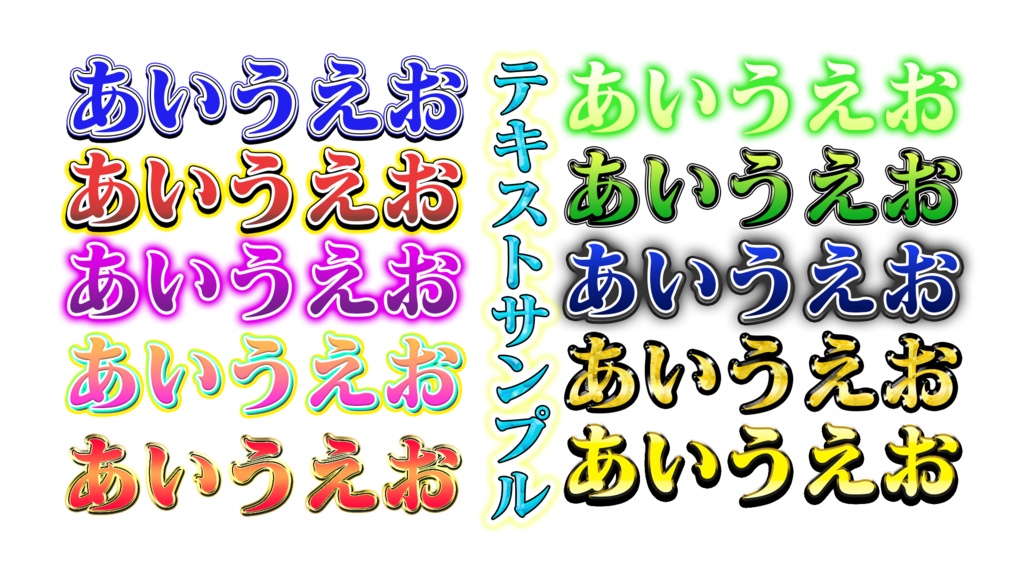
【テレビマンが使っているフォント20種類を"大特価"で大公開!】
大特価でテレビマンが使っているフォント21種類を大公開! 周りと差を付けるテロップデザインを求む方向け! Youtubeなどの動画制作など幅広く使えるデザインにしました♪ Photoshopのスタイルを読み込んで文字を変えるだけで簡単に使用できます! テロップのクオリティを2ランク上げたい時に使える便利な テンプレートを1から制作しました。 ・書体、色の変更次第で表現の可能性は無限大! 商用利用にもバンバンご使用ください! 利用規約 ■本製品は、サムネイル制作・動画編集におけるテロップ制作を主として作成しております。 ■非商用・商用問わず、ご自由にご利用いただけます。 ■ご利用時のご報告、提供などの表示は不要です。 仕様 ■制作バージョン:Adobe Photoshop ■カラーモード:RGB ■サイズ:1920×1080 解像度:72ピクセル